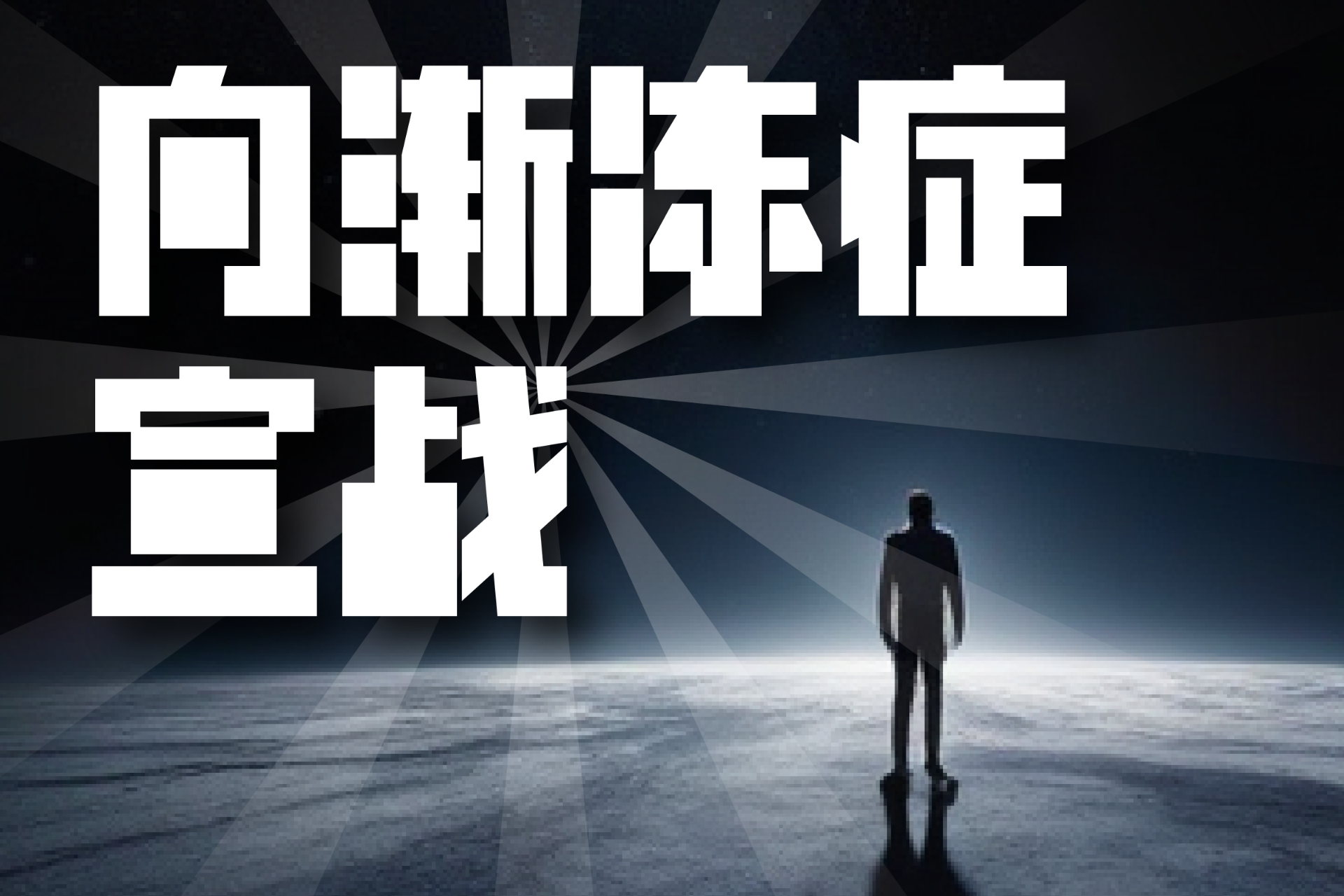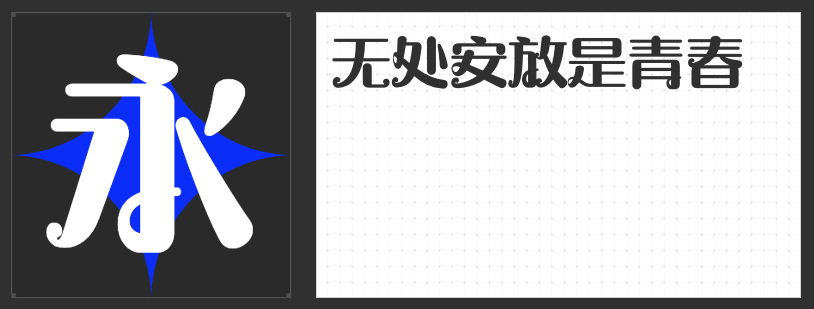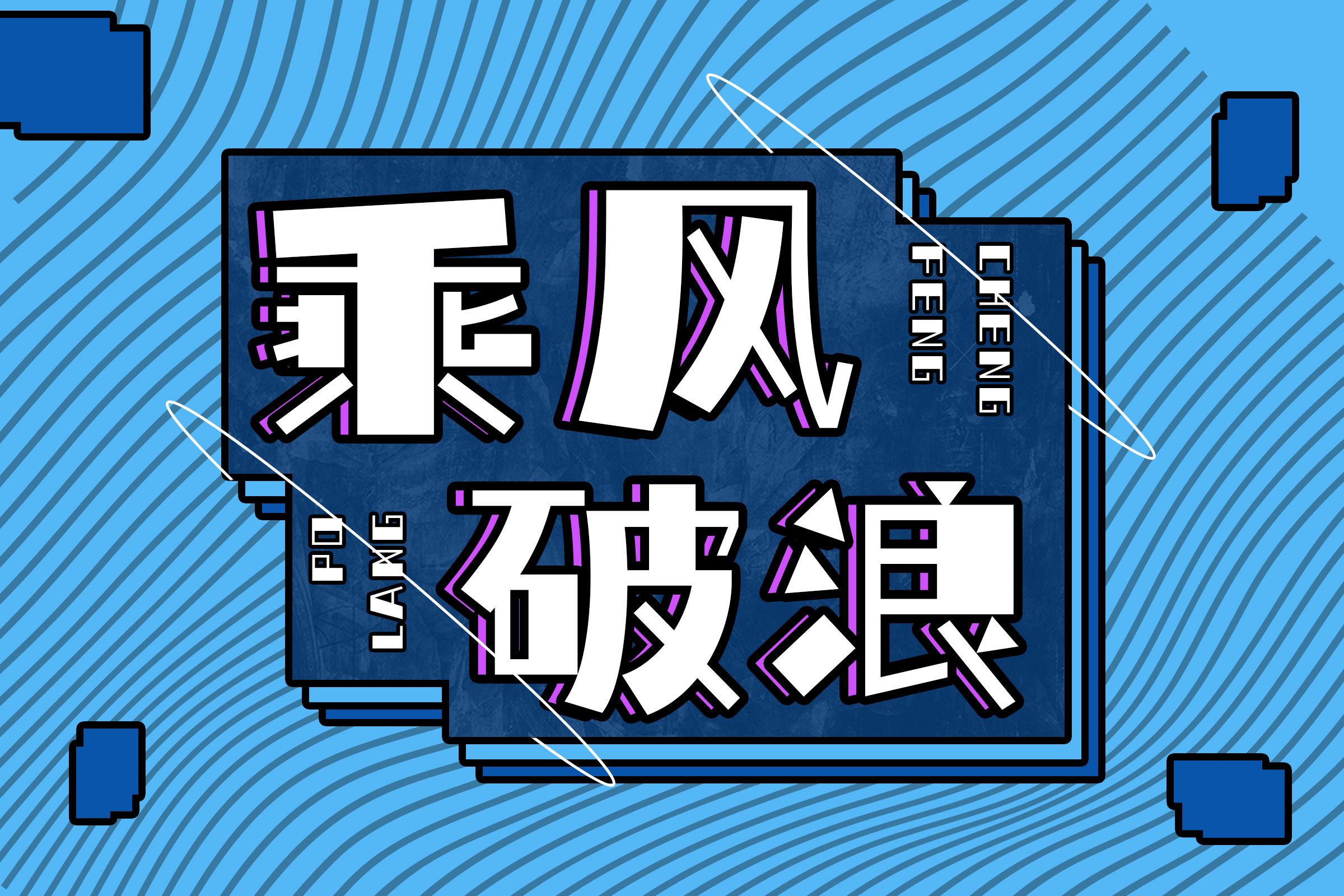
探索创意之巅:灵感加满的创意字体推荐
在数字化设计日新月异的今天,创意字体如同魔法般为视觉作品注入无限活力与个性。它们不仅仅是文字的简单排列,更是情感与信息的艺术化表达。以下,就为您推荐几款灵感加满的创意字体,让您的设计作品瞬间脱颖而出。
励字暴风简 超级黑
在追求视觉冲击力与情感共鸣的设计浪潮中,励字暴风简 超级黑如同一股不可阻挡的力量,脱颖而出成为创意字体界的新星。这款字体以其极致的粗黑线条,展现了无与伦比的力量感与现代感,仿佛每一次笔触都蕴含着激励人心的能量。
励字暴风简 超级黑不仅在视觉上给人以震撼,更在情感层面激发共鸣。它适用于多种场景,从励志海报到品牌标语,都能完美传达出坚定、自信、向前的信息。无论是希望激发团队士气的企业宣传,还是想要触动人心、鼓舞斗志的公益广告,励字暴风简 超级黑都能成为设计师手中的得力工具。
励字摩登圆简
在追求个性与创新的设计时代,励字摩登圆简以其独特的魅力脱颖而出,成为创意字体中的佼佼者。这款字体融合了摩登的时尚感与圆润的简约美。
励字摩登圆简不仅适用于现代感强烈的品牌标识、广告海报,还能在各类数字媒体中展现出独特的风格与气质。它的每一个字都像是精心雕琢的艺术品,既保持了文字的识别性,又增添了设计的艺术感。
喵字综艺体
在创意字体的广阔天地里,一款名为喵字综艺体的字体以其独特的萌趣风格,悄然成为设计界的新宠。其设计灵感源自舞台的璀璨光芒与动态韵律,每个字符都经过精心雕琢,既保留了传统汉字的神韵,又融入了现代综艺的灵动与不羁。
喵字综艺体不仅适用于综艺节目的海报、片头设计,还能为儿童读物、宠物用品等增添一抹不可抗拒的萌感。它的字形圆润可爱,色彩鲜明活泼,让人一眼就能感受到满满的趣味与亲和力。
喵字渐冻体
喵字渐冻体是一款具有深远意义的定制级字库产品,其设计初衷是为了让大众更加直观地了解渐冻症患者的痛苦与挣扎。
喵字渐冻体不仅适用于各种萌宠主题的设计,如宠物用品、猫咪咖啡馆的装饰、社交媒体上的萌宠分享等,还能为一些绘本、可爱风格的设计作品增添一抹独特的色彩。它能够让文字不仅仅是信息的载体,更成为视觉上的享受,让观者在阅读的同时,也能感受到一份来自心底的温暖与治愈。
创意字体,犹如设计师手中的魔法棒,能够赋予文字以生命,让设计作品更加生动有趣。选择适合的创意字体,就如同为设计披上了一袭华美的外衣,让信息的传达更加引人入胜。在这个充满无限创意的时代,让我们一起探索更多字体的可能,用文字书写属于未来的故事。